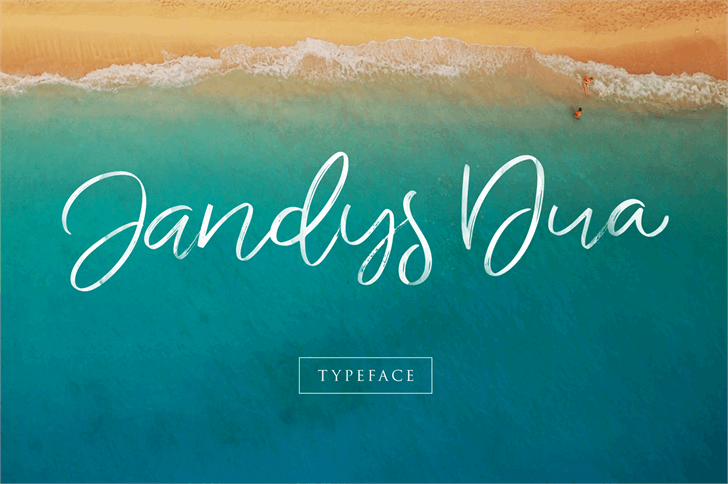
Introduzimos Jandys Typeface, uma fonte que transmite um estilo elegante e naturalmente autêntico, quase como escreveria com a mão. O seu traço rápido e fluido dá-lhe um aspecto suave e sofisticado, perfeito para design projetos com conceitos de elegância, casualidade e humor. Esta fonte é ideal tanto para criações de logotipo ou websites principais quanto para letras em cartões de casamento ou desenhos de citações. Seja onde você precise dela, Jandys Typeface estará sempre ao seu lado como a escolha perfeita para dar vida ao design que deseja. Alit Design é o criador desta fonte elegante e suave. Jandys Typeface está aqui para tornar sua arte ou projeto de design mais sofisticado e autêntico, combinando facilmente com qualquer tema que você queira expressar através do seu trabalho visual.